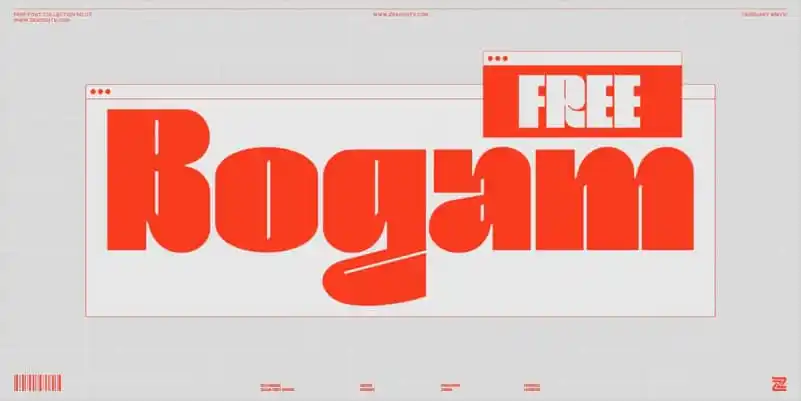
Bogam Display Font – Download Grátis
Bogam Display Font é uma herança urbana e vibrante que oferece um vasto leque de opções. Foi criada pelo talentoso designer Zea Fonts, inspirado no lifestyle moderno, a pulsante vida musical e o universo fashionista. Esta fonte apresenta um formato grande e fácil de ler, perfeitamente adaptável para aplicativos digitais e banners publicitários. Com seus caracteres maiúsculos e minúsculos, números e sinais de pontuação, Bogam é uma opção grátis que recompensa a criatividade dos designers. Ideal para estilos urbanos vibrantes, este recurso gráfico torna o seu trabalho ainda mais visualmente impactante. Seja para criar identidades digitais ou design de logotipos, a Bogam Display Font oferece um leque amplo de opções para expressar sua personalidade e estilo único no ambiente digital.